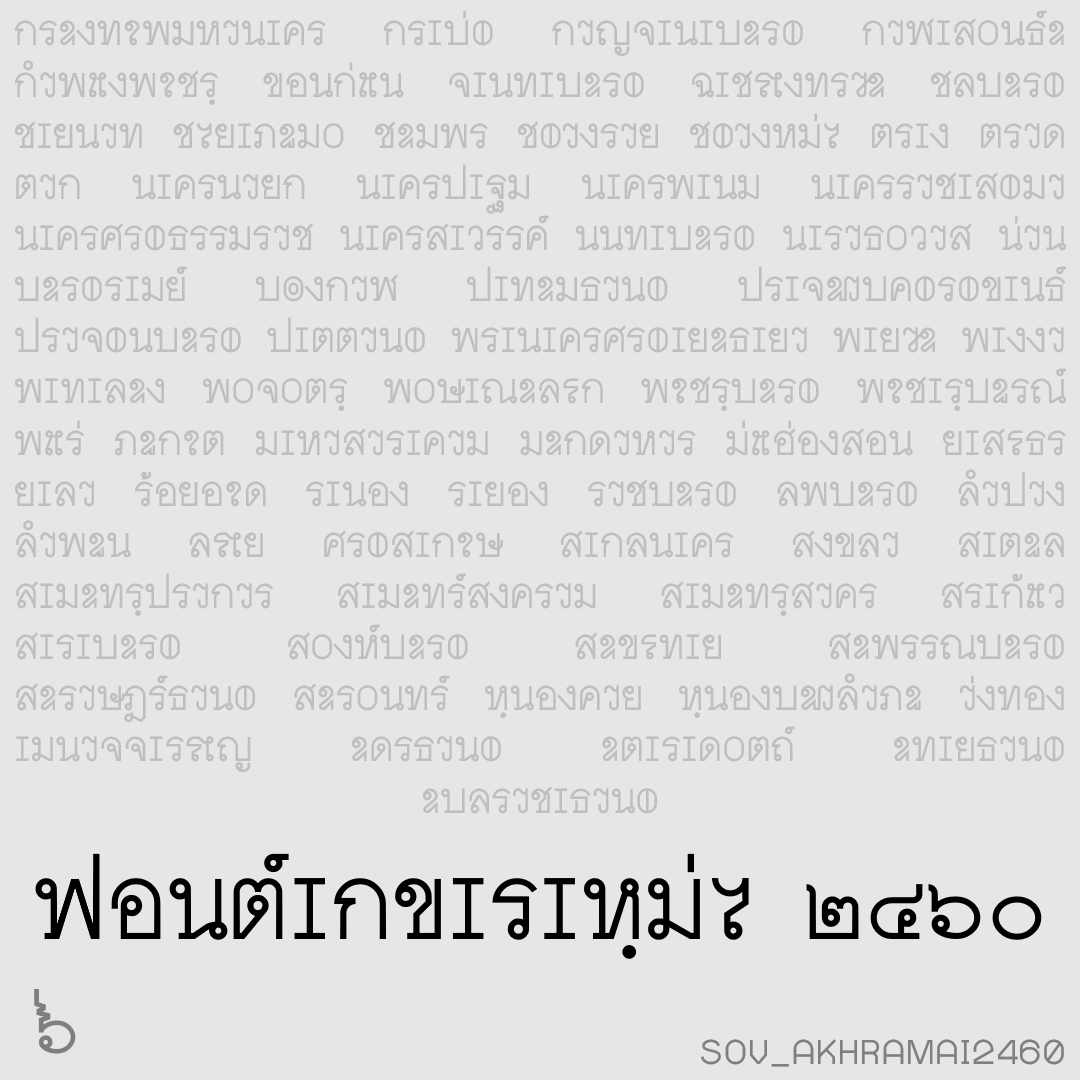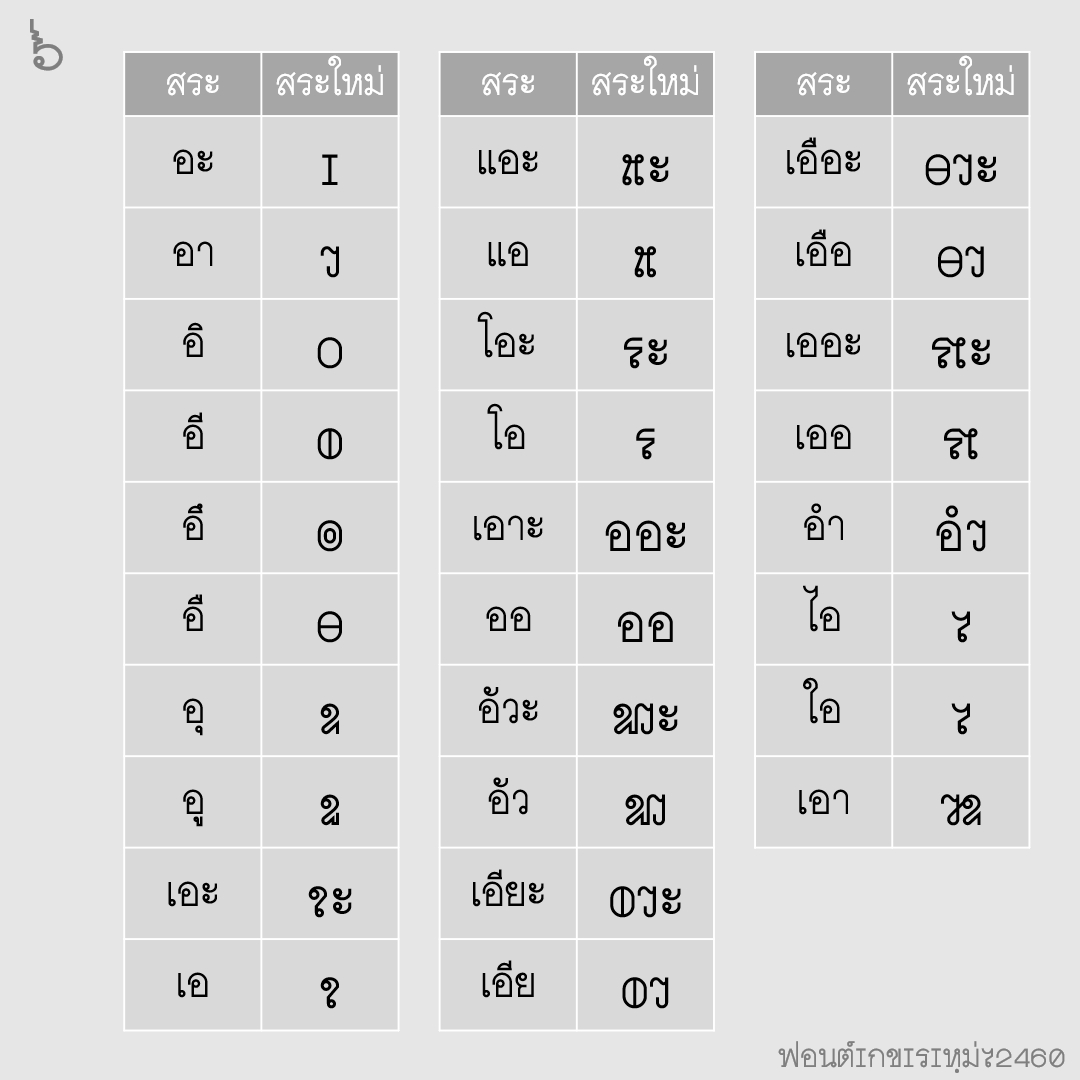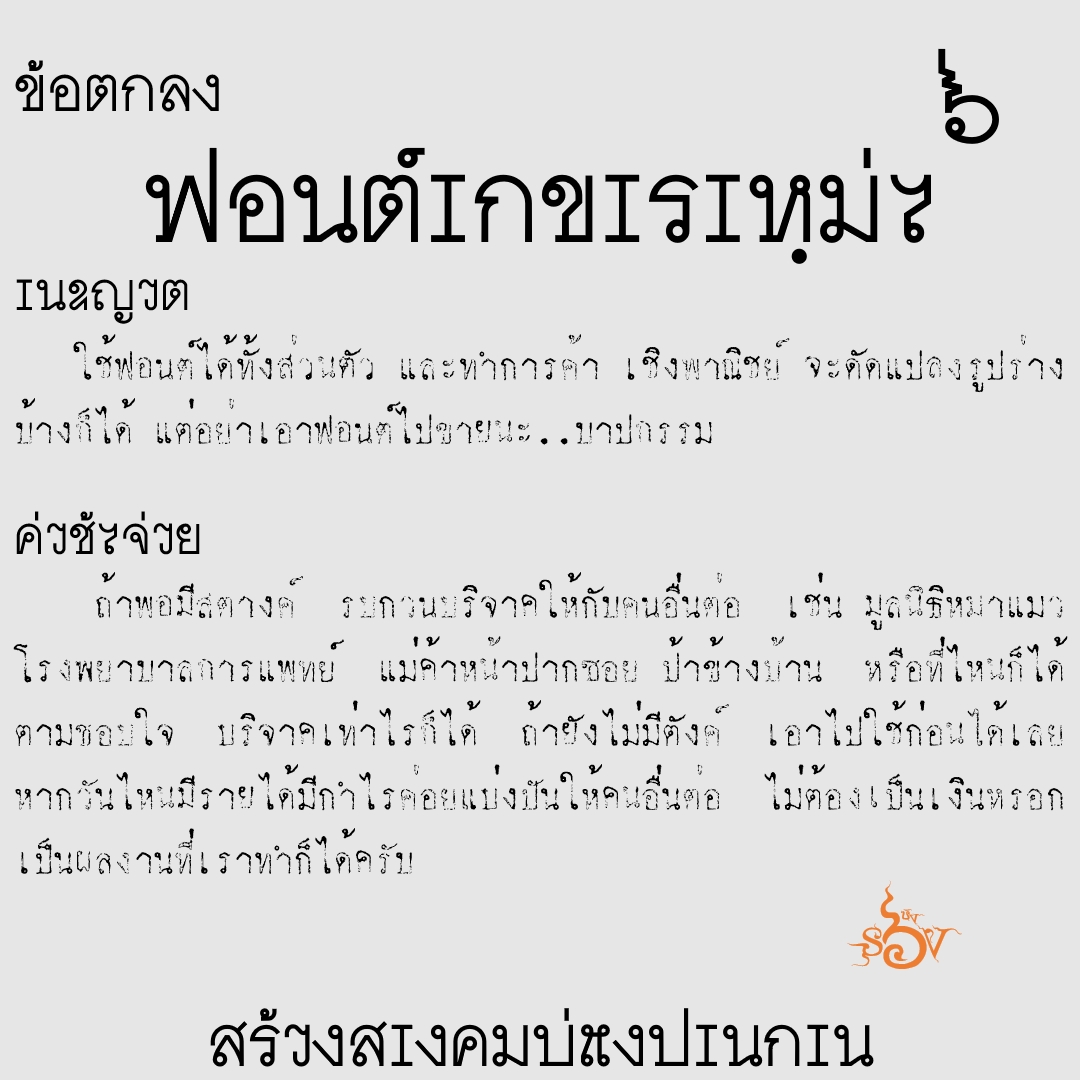
ชื่อฟอนต์ : อักขระใหม่๒๔๖๐
ทดลองสร้างฟอนต์ ตามอักขรวิธีใหม่ ที่ ร.๖ ได้ประทานพระบรมราชาธิบายต่อสมัคยาจารยสมาคม ในปี พ.ศ. ๒๔๖๐
หมายเหตุ ยังไม่คล่องใช้ฟอนต์ปรกติ คล่องแล้วหรือต้องการลบอักษรตัวเล็กๆ ใช้ฟอนต์หนา(bold)